Die Auswahl der Typografie für Ihre Website ist eine wichtige Entscheidung. Sie beeinflusst nicht nur den Gesamtstil der Website, sondern kann auch deren Benutzerfreundlichkeit beeinflussen. Angesichts der vielen Schriftartoptionen, Kombinationen und Layoutmöglichkeiten ist es leicht, etwas überfordert zu sein.
Glücklicherweise kann die Betrachtung einiger der neuesten Typografie-Trends Ihnen bei Ihrer Entscheidung helfen. Als zusätzlicher Vorteil kann die Einbeziehung einiger zeitgenössischer Stile verhindern, dass Ihre Website veraltet aussieht.
In diesem Artikel werden wir erörtern, warum Ihre Typografie-Wahl so wichtig ist. Anschließend werden wir zehn Typografie-Trends für 2022 vorstellen. Wir schließen mit einigen Tipps zur Anwendung dieser Trends auf Ihrer Website und teilen Orte, an denen Sie Inspiration finden können. Lassen Sie uns beginnen!
Die Bedeutung der Web-Typografie
Einfach ausgedrückt bezieht sich Web-Typografie darauf, wie Sie Text auf Ihrer Website anordnen. Sie umfasst alles von der Schriftartauswahl und -größe bis hin zur Anordnung Ihres geschriebenen Inhalts. Obwohl das Aussehen wichtig ist, geht es bei Web-Typografie um mehr als nur Ästhetik.
Durchdacht gewählte Web-Schriftarten können Ihrer Website helfen, sich abzuheben und zu Ihren gesamten Branding-Bemühungen beitragen. Typografie spielt auch eine Rolle bei der Benutzererfahrung (UX), da eine schwer lesbare Schriftart ein erheblicher Nachteil für Ihr Publikum sein kann.
Typografie ist eines der wichtigsten Elemente, die bei der Gestaltung einer Website zu berücksichtigen sind, da so viel vom Erfolg der Website davon abhängt. Es ist wahrscheinlich, dass jeder Teil Ihrer Website, von Inhalten über Navigation bis hin zu Formularen, Text enthält. Schlecht gewählte Typografie kann viel Reibung für Ihre Benutzer erzeugen, was zu verlorenen Konversionen führen kann. Das Hinzufügen zu vieler Schriftarten kann beispielsweise zu Verwirrung, Konzentrationsverlust und schlechter Benutzererfahrung führen. Um dies zu vermeiden, empfehlen wir die Verwendung von zwei Schriftarten, da dies die perfekte Menge für eine Website ist.
Im Gegensatz dazu kann die Kombination von Typografie mit anderen aktuellen Webdesign-Trends dazu beitragen, dass Ihre Website frisch und relevant aussieht. Es ist eine relativ einfache Möglichkeit zu zeigen, dass Sie Zeit und Mühe investieren, um Ihre Website auf dem neuesten Stand zu halten.
Liste der Top 10 Typografie-Trends für 2025
Nachdem wir die Bedeutung der Typografie für Ihre Website erörtert haben, lassen Sie uns nun zehn herausragende Typografie-Trends für 2025 betrachten.
1. Brutalistische Typografie
Der Brutalismus ist ein Stil, der in der Architektur entstand und sich üblicherweise durch harte, gerade Linien und einen Mangel an dekorativen Elementen auszeichnet. In der digitalen Typografie manifestiert er sich als große, imposante Beschriftung, die gelegentlich auf unerwartete Weise platziert wird.
Die heutige brutalistische Typografie ist etwas sanfter als in der Vergangenheit. Dennoch behält sie eine fesselnde und beeindruckende Ausstrahlung bei, wie Sie in folgendem Beispiel erkennen können:
Brutalistische Schriftarten harmonieren außerordentlich gut mit gedämpfteren Farben, was jedoch nicht bedeutet, dass Sie nicht durch die Verwendung eines leuchtenden Gelbs oder Pink für Abwechslung sorgen können. Tatsächlich könnte der nächste Trend, den wir betrachten, eine ausgezeichnete Gelegenheit bieten, eine brutalistische Schriftart einzusetzen.
2. Große und fette Überschriften
Ihre Überschriften auffällig und blickfangend zu gestalten, kann dazu beitragen, Ihre Botschaft zu vermitteln. Da fette Überschriften in diesem Jahr populär sind, können Sie dramatische Überschriften kreieren und gleichzeitig trendkonform bleiben.
Beispiele hierfür können Sie auf der Over Covid Website hervorgehoben sehen:
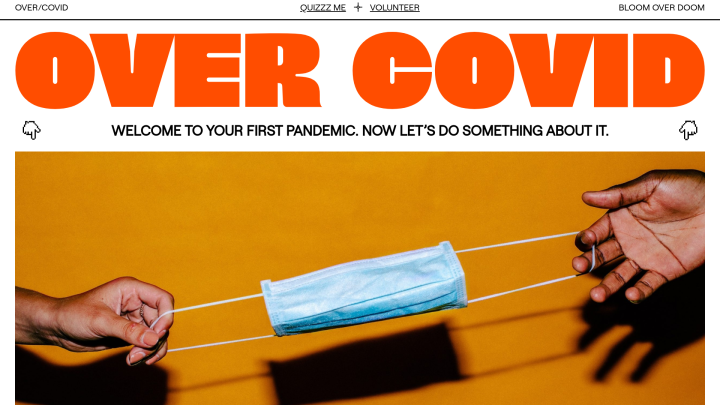
Da die meisten Webnutzer Inhalte überfliegen, anstatt sie eingehend zu lesen, sollten Sie sicherstellen, dass Ihre wichtigsten Botschaften hervorstechen. Versuchen Sie, eine unübersehbare Überschrift zu erstellen, um die Aufmerksamkeit Ihres Publikums zu fesseln. Einige Schriftarten, die sich gut für fette Überschriften eignen, sind Franklin Gothic und Benton Sans.
3. Umrissene Schriftarten
Umrissene Schriftarten können eine solide Ergänzung für Ihren Hero-Bereich sein. Sie können sie nutzen, um einen starken ersten Eindruck bei Ihren Besuchern zu hinterlassen.
Diese Schriftarten harmonieren gut mit schlichten Hintergründen:
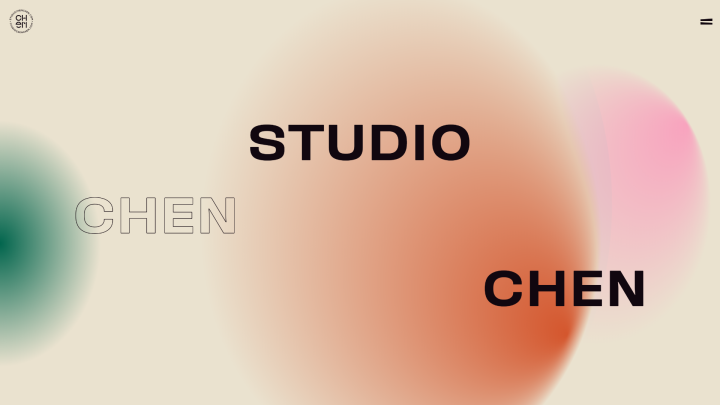
Es ist von besonderer Bedeutung, bei der Verwendung von umrissenen Schriftarten auf den Farbkontrast zu achten, da die Lesbarkeit beeinträchtigt sein kann. Sie könnten versuchen, umrissene Schriftarten mit fetten, ausgefüllten Texten zu kombinieren, um einen dramatischen Kontrast und eine starke Wirkung zu erzielen, wie Sie im obigen Beispiel sehen können.
4. Gebrochene typografische Layouts
Gebrochene typografische Layouts können Wörter auf unerwartete Weise kombinieren. Obwohl der Effekt störend sein kann, kann er bei korrekter Anwendung Aufmerksamkeit erregen, ohne die Lesbarkeit zu beeinträchtigen:
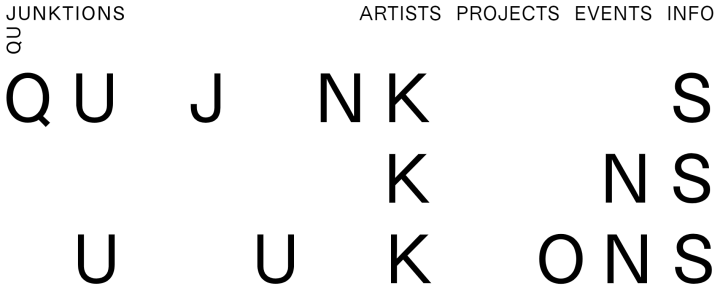
Gebrochene Typografie ist nützlich für Überschriften oder andere Texte, die Sie hervorheben möchten. Beachten Sie, dass diese Schriftarten je nach der spezifischen Wahl der Schriftart manchmal schwer zu lesen sein können. Daher sollten Sie möglicherweise vermeiden, sie für entscheidende Informationen zu verwenden.
5. Schwarz und Weiß
Minimalistisches Webdesign ist seit einiger Zeit ein Trend. Es ist daher nicht überraschend, dass saubere, schlichte schwarz-weiße Typografie in 2025 in Erscheinung tritt:
Obwohl er für seine Einfachheit bekannt ist, muss Minimalismus nicht langweilig sein. Sie könnten versuchen, Schwarz und Weiß auf unaufdringliche Weise zu kombinieren, indem Sie abwechselnd das eine für den Text und das andere für den Hintergrund verwenden. Das obige Beispiel verwendet zwei sehr unterschiedliche Schriftarten, um einen eleganten und dennoch aufregenden Effekt zu erzielen.
6. Überlagern oder Vermischen von Text und Bildern
Das Überlagern von Text über Bilder oder andere Elemente kann Ihrem Inhalt eine zusätzliche Bedeutungsebene verleihen. In diesem Beispiel wird ein farbiger Filter über das Bild gelegt, um die Lesbarkeit zu verbessern:
Durch die Kombination mehrerer Ebenen können Sie einen dreidimensionalen Effekt erzielen. Sie könnten sogar einen Schritt weitergehen und Text und Bilder gründlich vermischen.
Es ist jedoch von entscheidender Bedeutung sicherzustellen, dass der Effekt keine wichtigen Informationen verdeckt. Sie könnten versuchen, verschiedene Farben in Ihrem Text zu verwenden, damit Ihre Worte nicht mit dem Hintergrund verschmelzen.
7. Psychedelische Farben
Dieser unterhaltsame Retro-Trend ist so farbenfroh wie nur möglich. Sie können mit den psychedelischen Farben wirklich kreativ werden und viel Aufregung in Ihre Website bringen, wie es Special Offer, Inc. getan hat:
Das Hinzufügen eines regenbogenfarbenen Batik-Effekts als Hintergrund ist eine lebendige Möglichkeit, schwarzen oder weißen Text hervorzuheben. Sie könnten auch amüsante, psychedelische Farben in den Text selbst integrieren, wobei Sie auf den Kontrast achten sollten.
8. Fette, niedrige Schriftarten
Diese Schriftarten haben eine niedrige x-Höhe, was bedeutet, dass sie tendenziell etwas breiter als hoch sind. Dies führt zu klobigen Buchstaben, die hervorstechen.
Brandon Grotesque ist eine beliebte Schriftart dieses Stils:
Diese Schriftarten funktionieren gut, wenn ausreichend Platz vorhanden ist, um die Lesbarkeit zu gewährleisten. Sie werden wahrscheinlich einen angemessenen Abstand zwischen Buchstaben und Wörtern beibehalten wollen. Während solche Schriftarten vermutlich nicht die beste Wahl für einen gesamten Blogbeitrag wären, eignen sie sich gut für Überschriften oder kurze Hervorhebungen.
9. Glitch-Text
Glitch-Text kann Ihrer Website ein kantiges, künstlerisches Element hinzufügen. Die Verwendung kann herausfordernd sein, kann aber viel Energie und Einzigartigkeit in Ihren Hero-Bereich bringen:
Da dieser Stil absichtlich schwer zu lesen ist, sollten Sie seinen Einsatz begrenzen. Indem Sie Glitch-Text in Maßen einsetzen, erzielen Sie eine signifikante visuelle Wirkung, ohne wichtige Informationen zu verschleiern. Andererseits, wenn Sie sich nicht übermäßig um die Lesbarkeit sorgen, sind Glitch-Schriften ein ausgezeichneter Kandidat für die Kombination mit Animation.
10. Animierte Typografie
Animierte Typografie ist ein exzellentes Werkzeug, um die Aufmerksamkeit des Lesers zu fesseln und zu halten. Das Hinzufügen von etwas Animation zu einer Website kann Ihren Inhalt ansprechender gestalten, wie Sie auf der SurveyMonkey-Startseite sehen können:
Sie haben nahezu endlose Möglichkeiten, wenn es um Animation geht. Einige beliebte Optionen sind:
- Scrollender Text über den Bildschirm.
- Fliegende Buchstaben von außerhalb des Bildschirms.
- Ändern der Form wichtiger Buchstaben beim Überfahren mit der Maus.
- Text, der aus dem Hintergrund verblasst.
Wenn Sie sich entscheiden, Ihren Text zu animieren, stellen Sie sicher, dass die gewählte Schriftart einfach und leicht zu lesen ist. Sie sollten auch einen Alternativplan haben, damit Benutzer auf Ihren Inhalt zugreifen können, selbst wenn die Animation nicht funktioniert.
Wie Sie Typografie-Trends in Ihrem Webdesign anwenden
Bei der Gestaltung der Typografie für eine Website, die Sie erstellen, ist es hilfreich, über die Stimme Ihrer Marke sowie über das nachzudenken, was Sie durch Ihren Text kommunizieren werden. Bedenken Sie, dass Typografie ein wunderbarer Ausdruck der Persönlichkeit einer Marke sein kann.
Während Trends aufregend und sehr unterhaltsam sein können, könnten zu viele konkurrierende Stile Probleme in Ihrem Design verursachen. Wenn Sie versuchen, jeden Trend einzubauen, werden Sie wahrscheinlich feststellen, dass Ihre Website unordentlich und verwirrend aussieht, seien Sie also vorsichtig beim Schriftpaaren. Versuchen Sie, sich auf einen Trend oder vielleicht zwei, die gut zusammenpassen, zu beschränken.
Dieses Beispiel verwendet im Hauptteil des Inhalts durchgehend dieselbe Schriftart. Es kombiniert jedoch die Trends von Umrissschriften und Schwarz-Weiß. Das Ergebnis ist schlicht, aber ansprechend:
Versuchen Sie, organisiert zu bleiben und ein klares Designsystem für Ihre Typografie zu erstellen, um die Konsistenz über Ihre gesamte Website sowie Visitenkarten oder Flyer hinweg zu bewahren. Das Hinzufügen von Richtlinien für Typografie zu Ihrem Styleguide kann Ihnen helfen, auf Kurs zu bleiben.
Wo Sie großartige Typografie-Inspiration finden
Wenn Sie sich festgefahren fühlen, gibt es im Web zahlreiche inspirierende Beispiele, die Sie erkunden können. Sie könnten sich sogar entscheiden, eine benutzerdefinierte Schriftart auf Ihrer Website zu verwenden.
Sie können sich Elementors monatliche Präsentation ansehen. Hier finden Sie sorgfältig kuratierte Websites, die mit Elementor erstellt wurden. Jeden Monat konzentriert sich unsere Präsentation auf ein anderes Thema, wie einseitige Websites oder Hochzeitswebsites:
Elementor verfügt auch über eine Vorlagenbibliothek, die Sie zur Inspiration durchsuchen können. Wir haben Kits und Vorlagen für verschiedene Website-Elemente in einer großen Auswahl von Branchen verfügbar:
Design Shack ist ein Online-Magazin für Webdesigner und Entwickler. Sie finden hier viele umsetzbare Informationen sowie eine Design-Galerie:
Wir empfehlen Ihnen außerdem, die typografischen Trends auf Websites, die Sie häufig besuchen, zu beobachten. Sobald Sie beginnen, der Typografie besondere Aufmerksamkeit zu schenken, werden Sie möglicherweise von der Menge an Kreativität überrascht sein, die Sie entdecken.
Typografie für und darüber hinaus
Typografie kann viele Aspekte einer Website beeinflussen, von der Markenbildung bis hin zur Benutzerfreundlichkeit. Ihre Wahl der Schriftarten und die Art und Weise, wie Sie Text mit dem Rest Ihrer Medien kombinieren, können einen nachhaltigen Eindruck bei den Besuchern hinterlassen.
Wenn Ihre Hauptsorge der Lesbarkeit gilt, möchten Sie möglicherweise bei einer brutalistischen Typografie bleiben. Für einen kantigeren Look könnten Sie versuchen, etwas glitschigen Text hinzuzufügen, insbesondere in Ihrem Hero-Bereich.